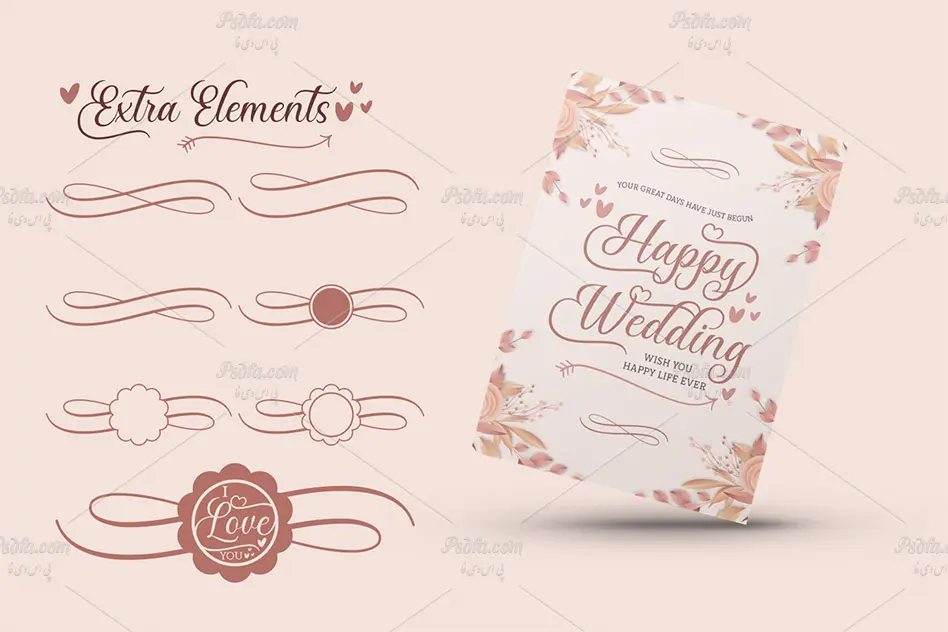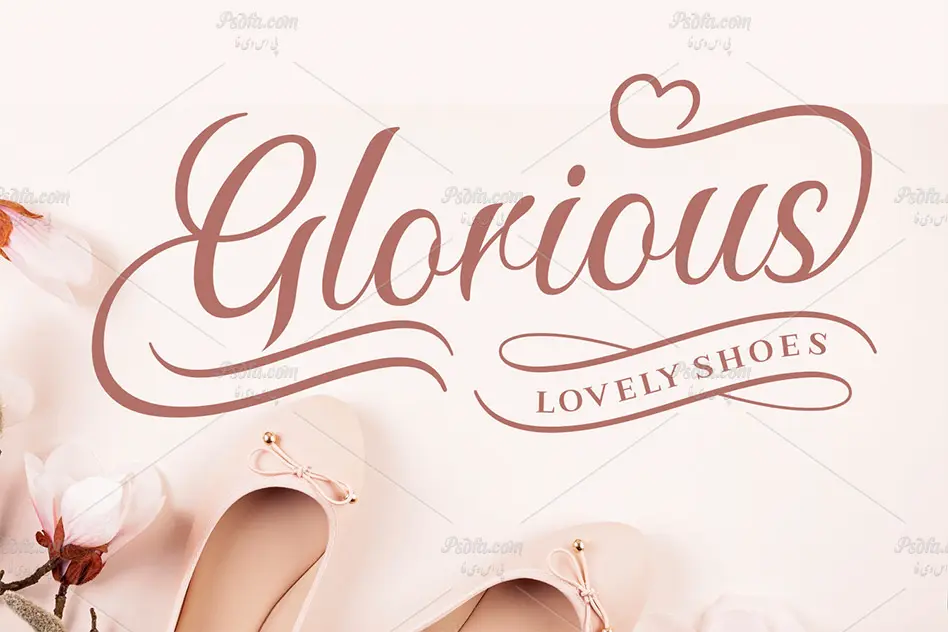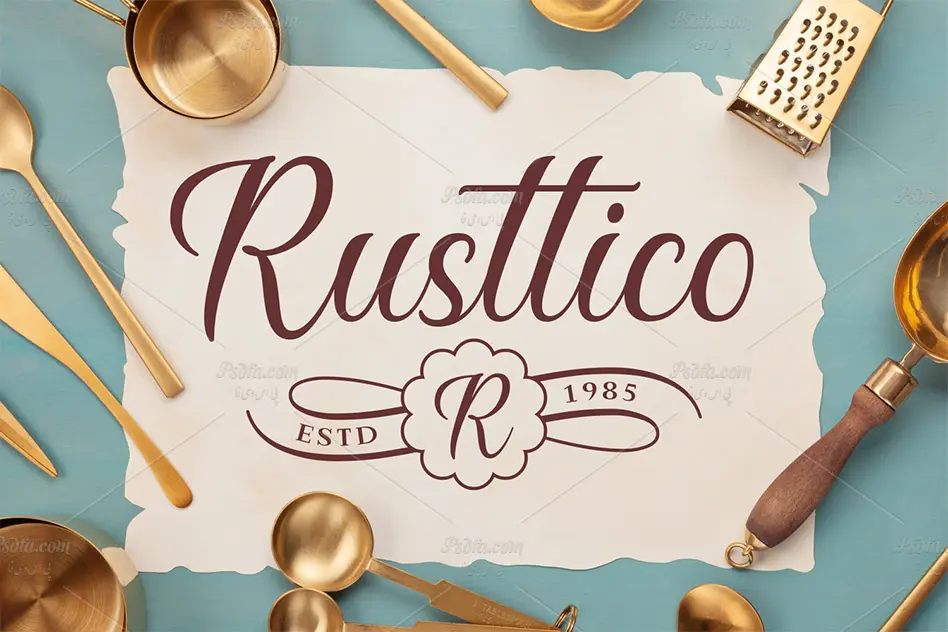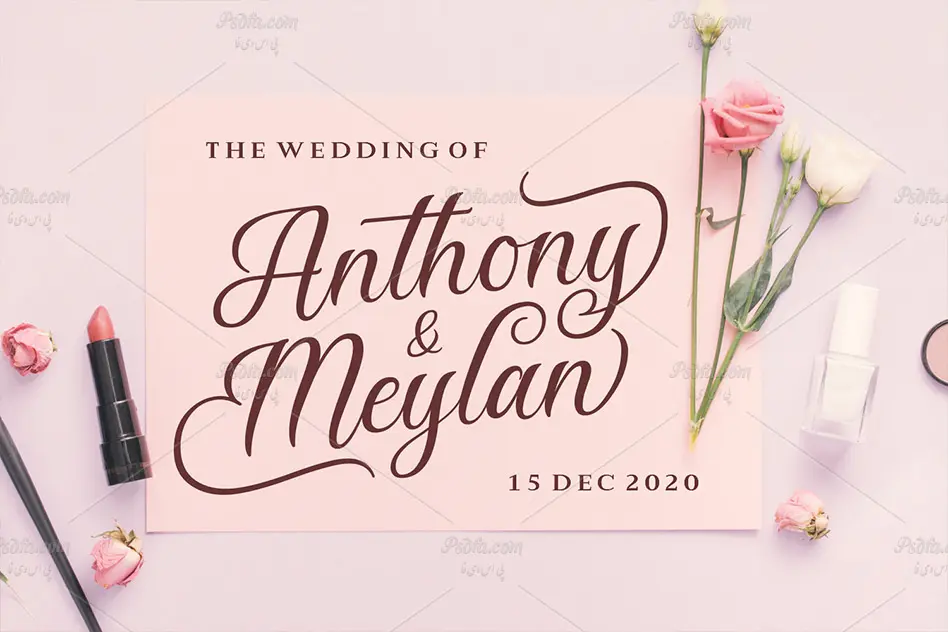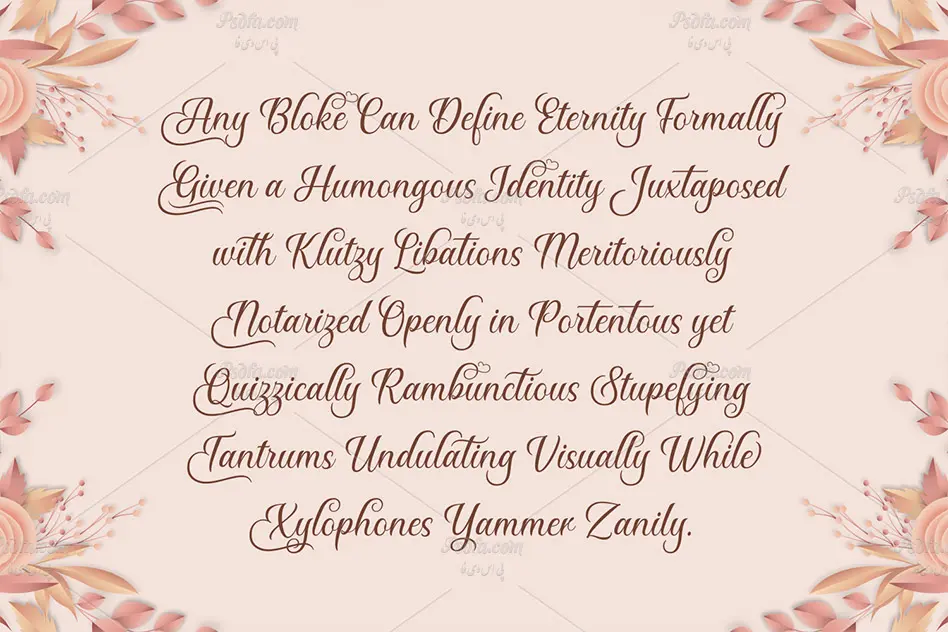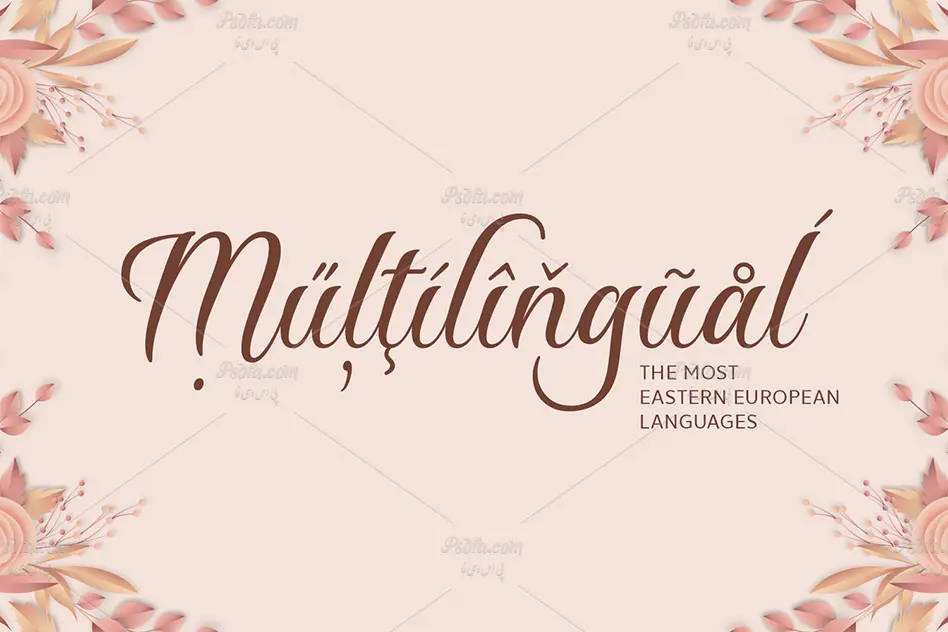
در این مطلب شاهد اسکریپت فونت زیبای Say Yes مناسب جهت استفاده در طراحی و گرافیک به خصوص ایجاد طرح های رمانتیک و عاشقانه می باشید. توسط این فونت انگلیسی زیبا که در قالب یک فایل otf بر روی سایت بارگذاری شده است می توان طرح هایی زیبا و رمانتیک ایجاد کرد. همچنین با نصب این فایل در پوشه فونت های سیستم قادر خواهید بود از آن در تمام نرم افزارهای گرافیکی و ویریشگر متن از جمله نرم افزار فتوشاپ ، افترافکت ، پریمیر ، مجموعه نرم افزار آفیس و … استفاده کنید. فونت Say Yes در وزن معمولی (Regular) ایجاد شده است که مناسب جهت طراحی انواع کارت تبریک ، کارت پستال ، کارت دعوت ، طراحی انواع پوستر ، کارت ویزیت ، تراکت ، بروشور و … می باشد.
- نام فونت : Say Yes
- وزن : معمولی (Regular)